Tendances typographiques.
Les nouveautés du Studio Monotype en design typographique.
Le design typographique est en constante évolution, il avance au rythme de la technologie et se développe au gré des attentes des consommateurs. Pour les marques et les créatifs qui cherchent à rester à la page, cela peut être difficile à suivre. Voici tout ce que vous avez besoin de savoir sur les mouvements actuels en typographie.
Tendances typographiques : découvrez le rapport.
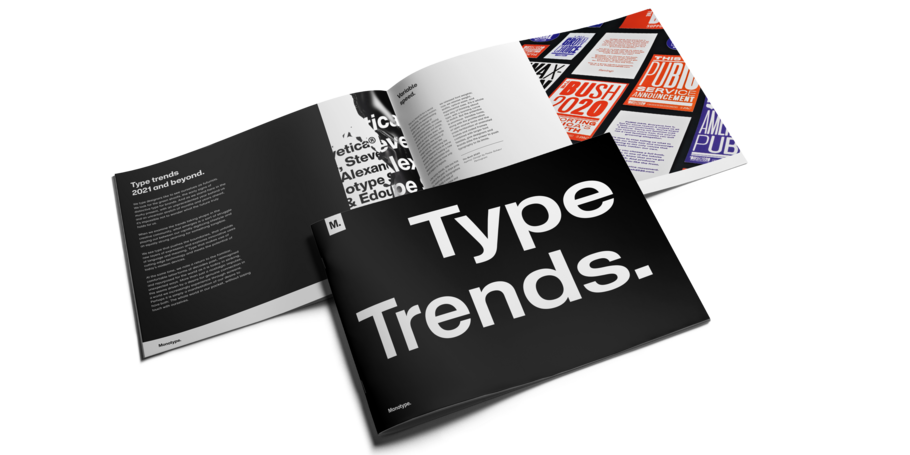
Pour présenter les tendances incontournables et les meilleurs exemples de leur mise en pratique, le Studio Monotype a passé au peigne fin les récents rebrands, les nouveaux projets et les utilisations fascinantes de la typographie.
Des serifs sinueux au texte d’affichage façon 80’s, de la technologie variable à l’austérité d’un « Helvetica-not-Helvetica », tous les styles et toutes les innovations qui influencent le secteur créatif d’aujourd’hui sont là.
Tendances typographiques 2021 et au-delà.
Les tendances en détail.
Des serifs soft-serve aux polices variables, de nombreuses découvertes vous attendent dans notre rapport sur les tendances typographiques.
Retrouvez des exemples de ces tendances en action, profitez des avis d’experts sur les innovations technologiques à l’origine d’utilisations typographiques nouvelles et passionnantes, découvrez comment la pandémie a modifié certains comportements de consommateurs et comment le design aide les marques à rester connectées à leurs clients, où qu’ils soient.
Pourquoi les marques adorent les polices sans serif (et comment choisir la vôtre)
Vous savez ce qu’on dit : « Les grands classiques ne se démodent jamais. » C’est peut-être vrai, peut-être pas. Mais une chose est sûre, lorsque les polices sans serif (dénuées d’empattement) ont débarqué dans les ateliers de typographie au début des années 1900, ce n’était pas juste par effet de mode, mais bien pour rester.
Alors que les entreprises continuent d’augmenter leur offre numérique dans le contexte de la pandémie de Covid-19, de nombreux designers, marques et agences se tournent vers les polices de caractères variables. Mais pour beaucoup, la question demeure : Que sont les polices variables et quel est le potentiel des polices variables pour transformer notre façon de communiquer sur le web ?
Comment une police peut aider vos clients à se sentir comme chez eux.
Lorsqu’il s’agit de votre marque, vos clients ne se contentent pas d’évaluer votre logo, vos couleurs ou la typographie, ils évaluent la façon dont votre marque les touchent. Plus que tout, les marques sont construites sur des sentiments - toute la réflexion que vous mettez dans le design et l’expérience sont simplement au service de la création d’un ressenti.
Ce qu’une marque devrait savoir sur les polices variables.
Découvrez comment les polices variables peuvent aider les marques qui cherchent à se distinguer sur le marché actuel.